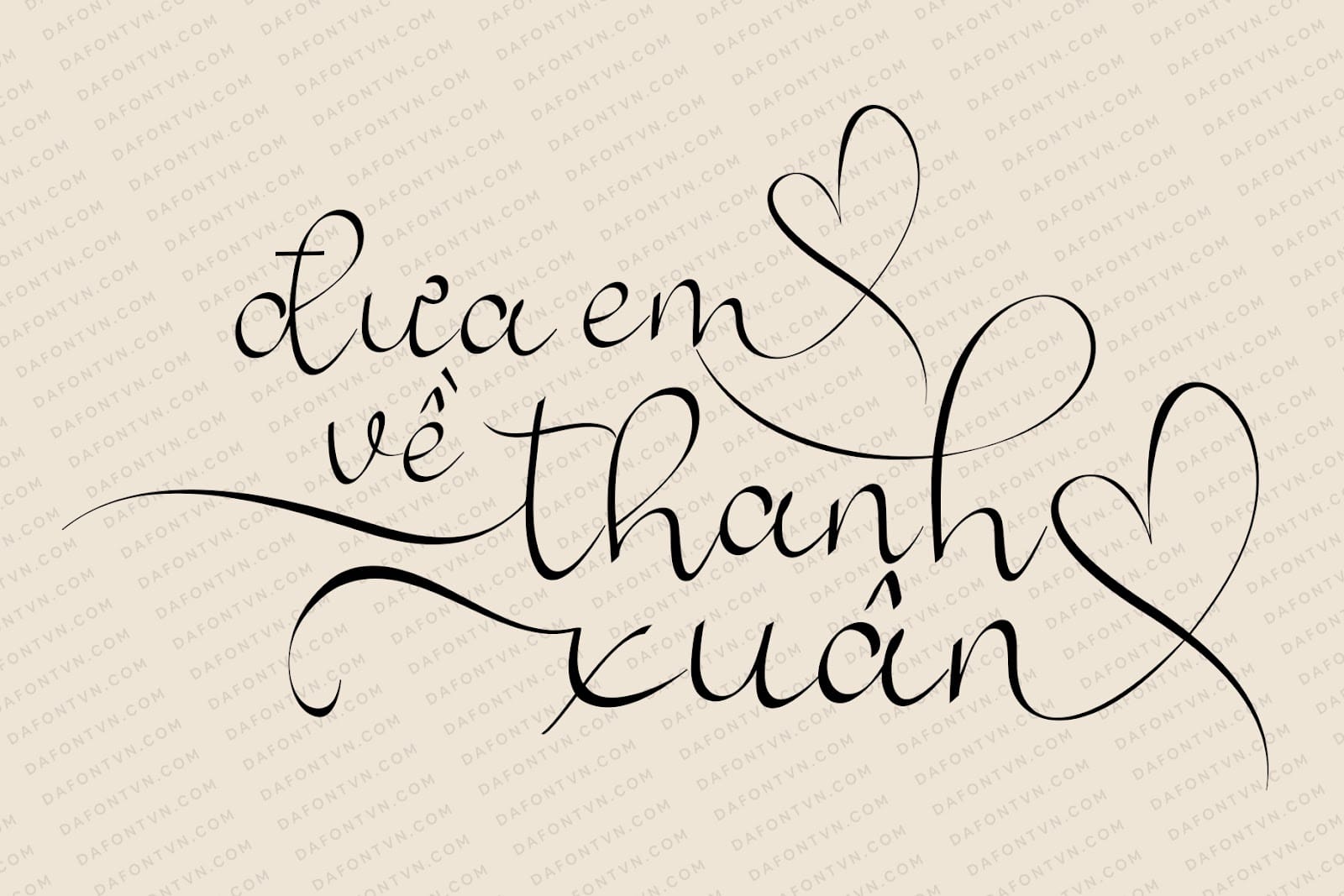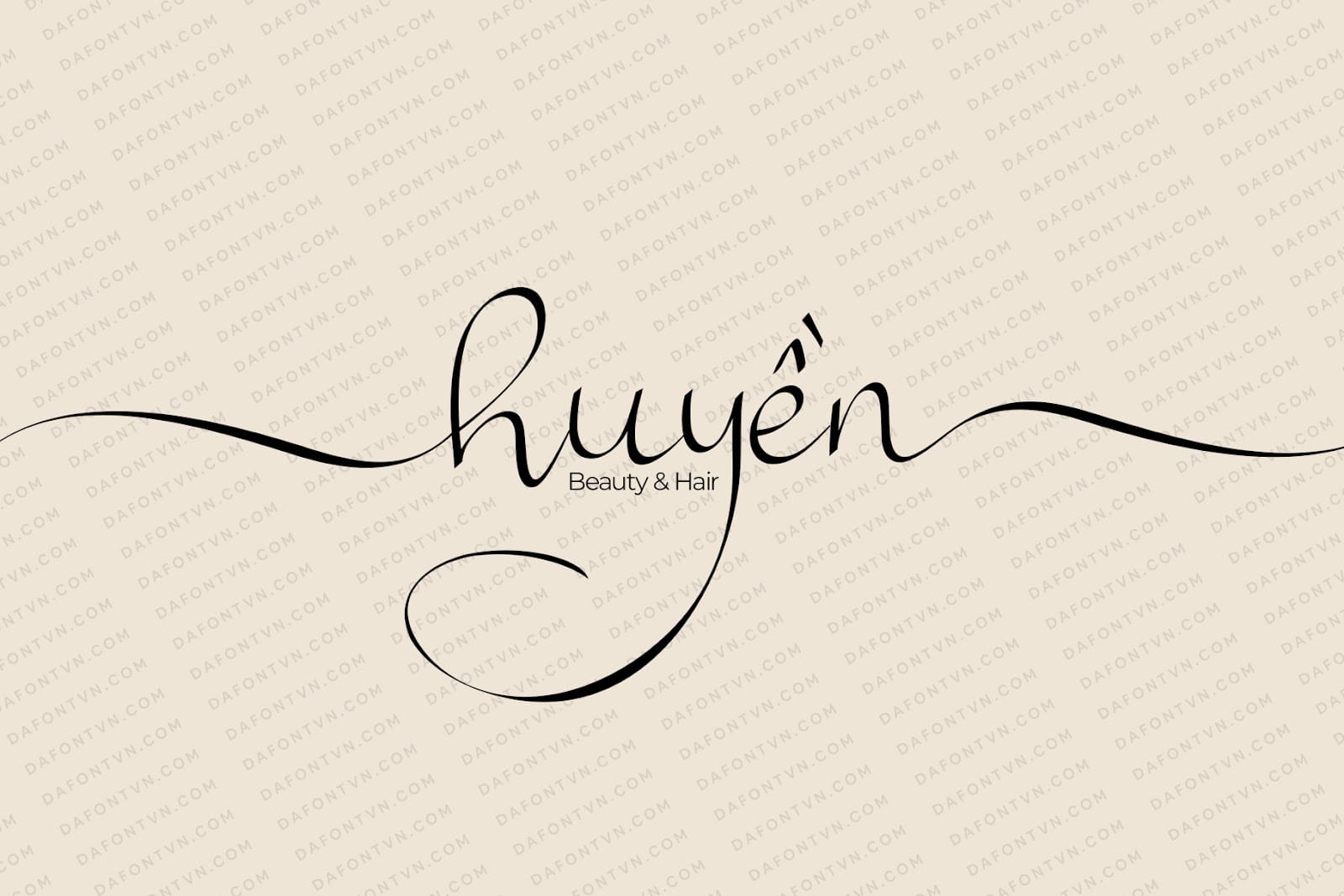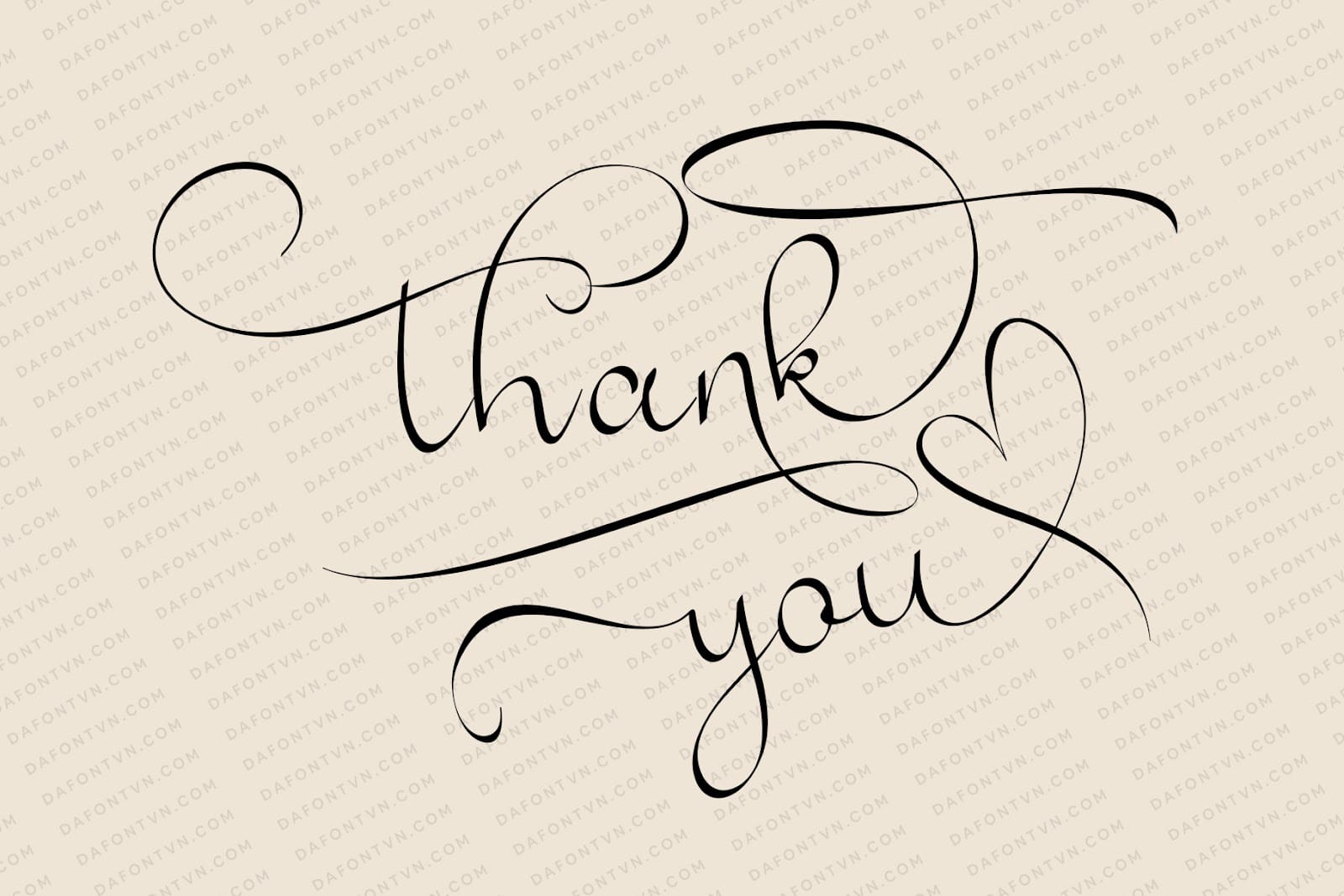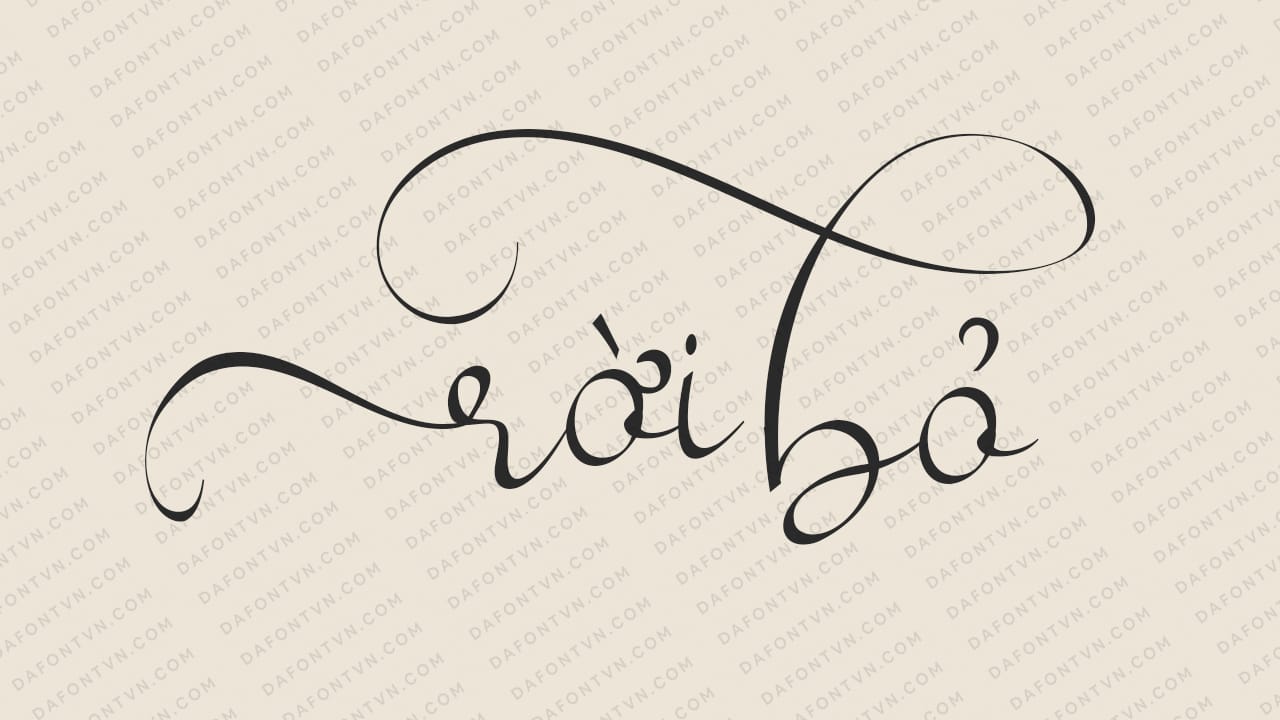
Ajibon – Font chữ thư pháp viết tay cực đẹp, được lấy cảm hứng từ chữ thư pháp viết nguệch ngoạc trên giấy rồi được làm lại thành chữ viết tay hiện đại và quyến rũ với những đường cong và độ dày nét rất sang trọng.
Bạn có thể sử dụng Ajibon cho nhiều mục đích thiết kế khác nhau như tiêu đề, chữ ký, logo, thư, thẻ tên, thiệp mời đám cưới, bảng hiệu, nhãn, áp phích, huy hiệu, v.v.
Đặc biệt Ajibon còn chứa đầy các chữ thường và chữ hoa, một loạt dấu câu, chữ số và hỗ trợ đa ngôn ngữ. Phông chữ này cũng chứa rất nhiều chữ ghép, các lựa chọn thay thế và phong cách khác nhau cho mỗi ký tự thường, bạn có thể kết hợp để tạo ra nhiều kiểu chữ khác nhau đẹp mắt thông qua bảng glyph trên Photoshop, Adobe Illustrator, Corel Draw và Adobe InDesign.